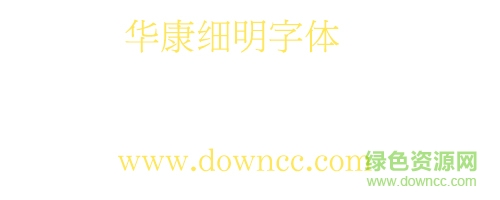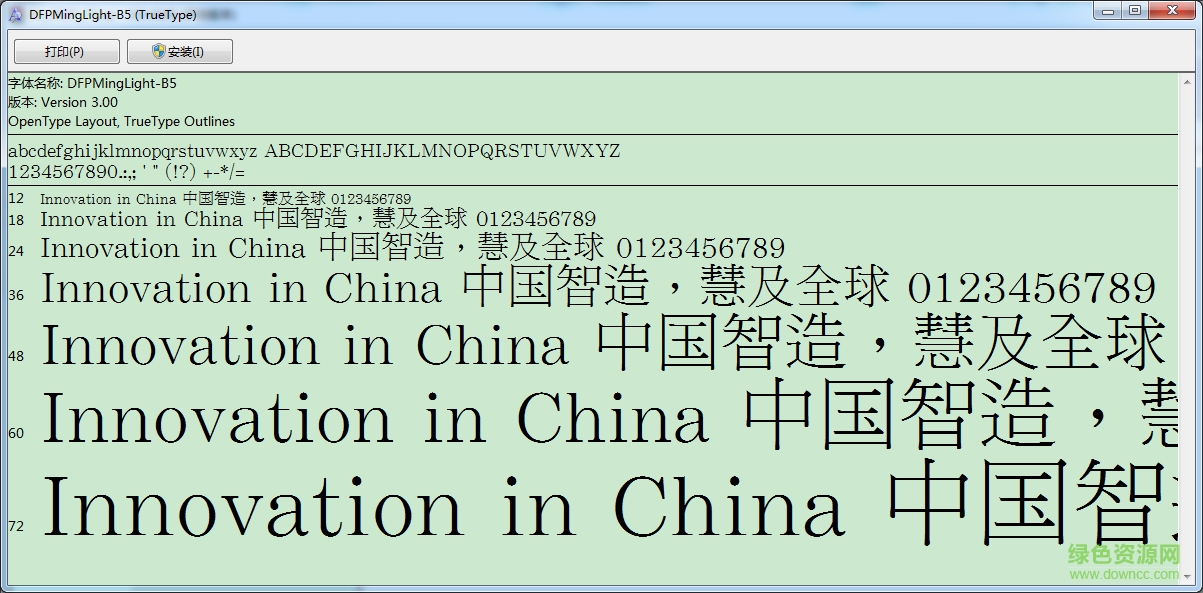
華康細(xì)明體是華康字體庫(kù)里的一款經(jīng)典字體,這款字體線條纖細(xì),字形優(yōu)美,整體效果非常的漂亮,喜歡的朋友趕緊來綠色資源網(wǎng)下載使用吧!
應(yīng)用于廣告創(chuàng)意設(shè)計(jì)方面的簡(jiǎn)體中文字體,該字體大方得體,字庫(kù)完整,整體風(fēng)格非常出色,可以適用于名片設(shè)計(jì)、平面設(shè)計(jì)、廣告設(shè)計(jì)、報(bào)紙雜志、企業(yè)LOGO、商標(biāo)注冊(cè)、電視臺(tái)廣告等領(lǐng)域,有喜歡的網(wǎng)友可免費(fèi)下載收藏。